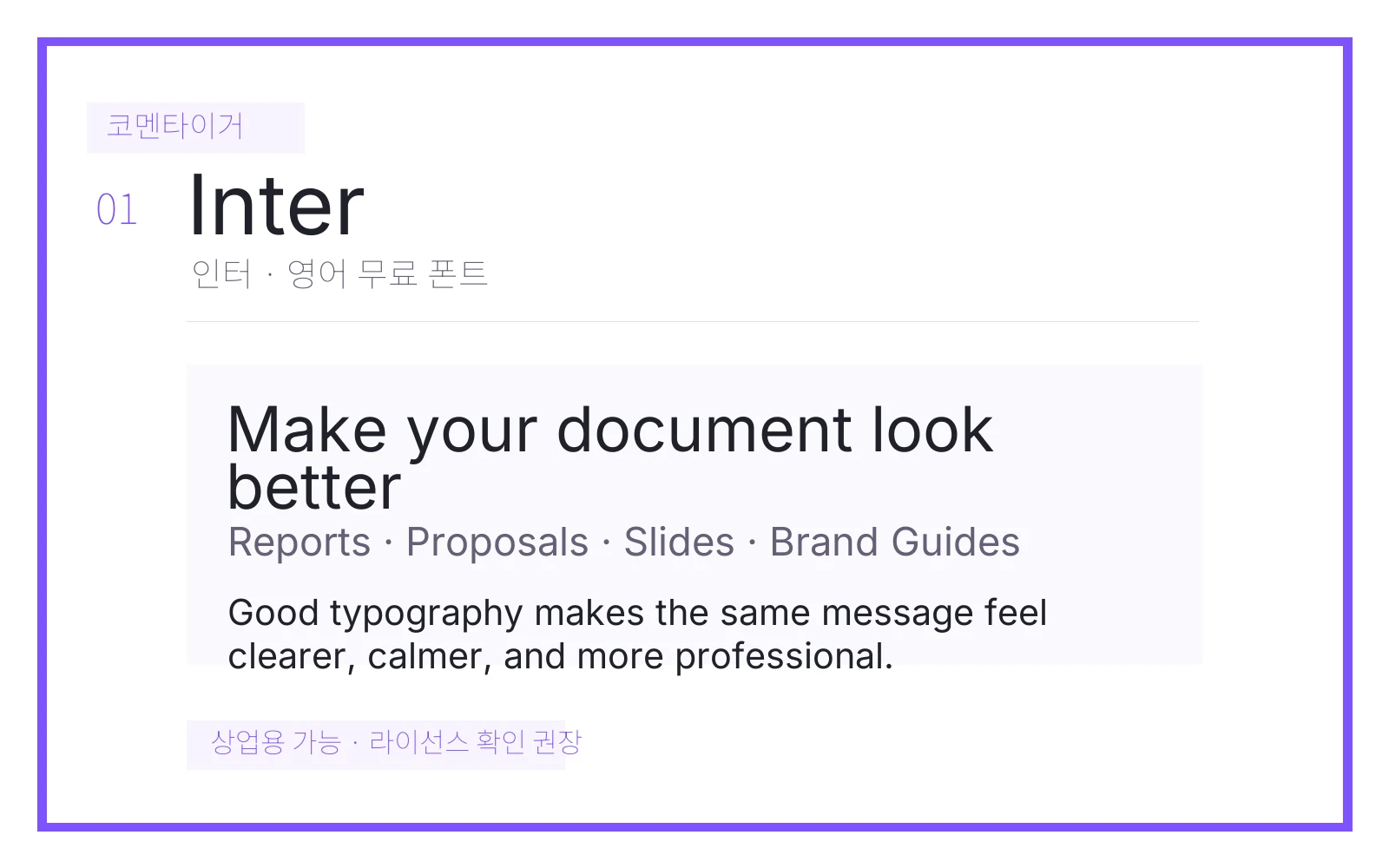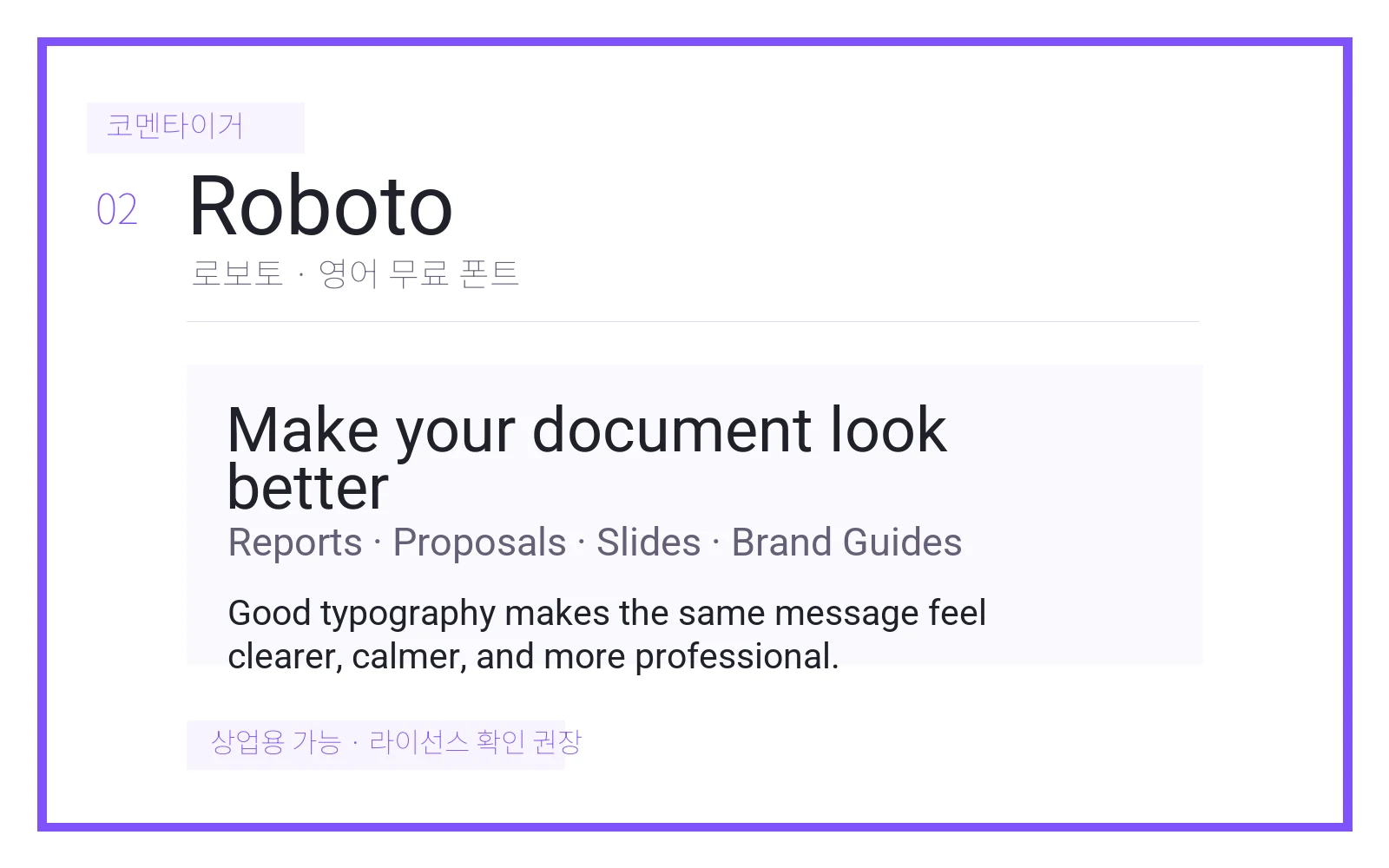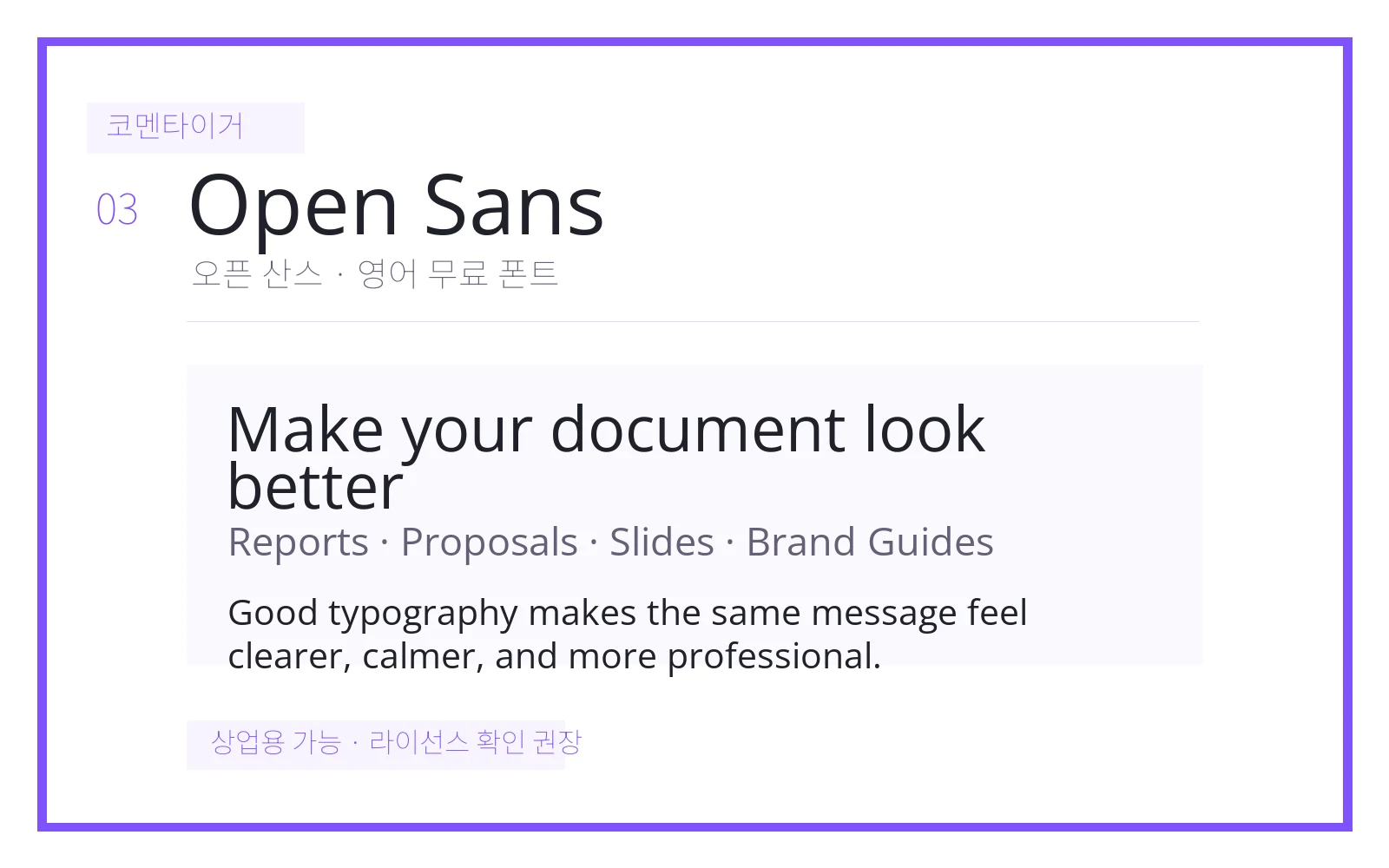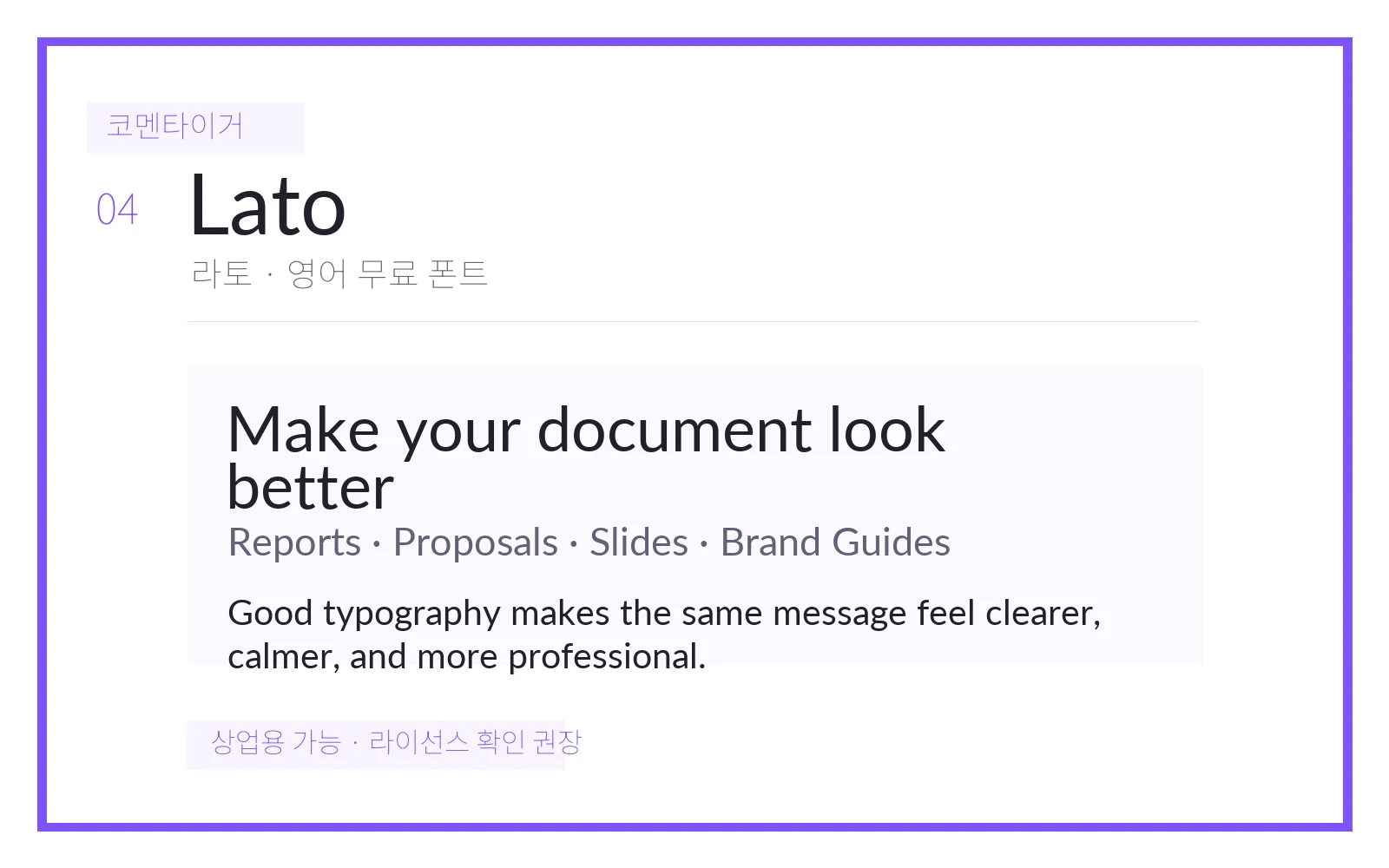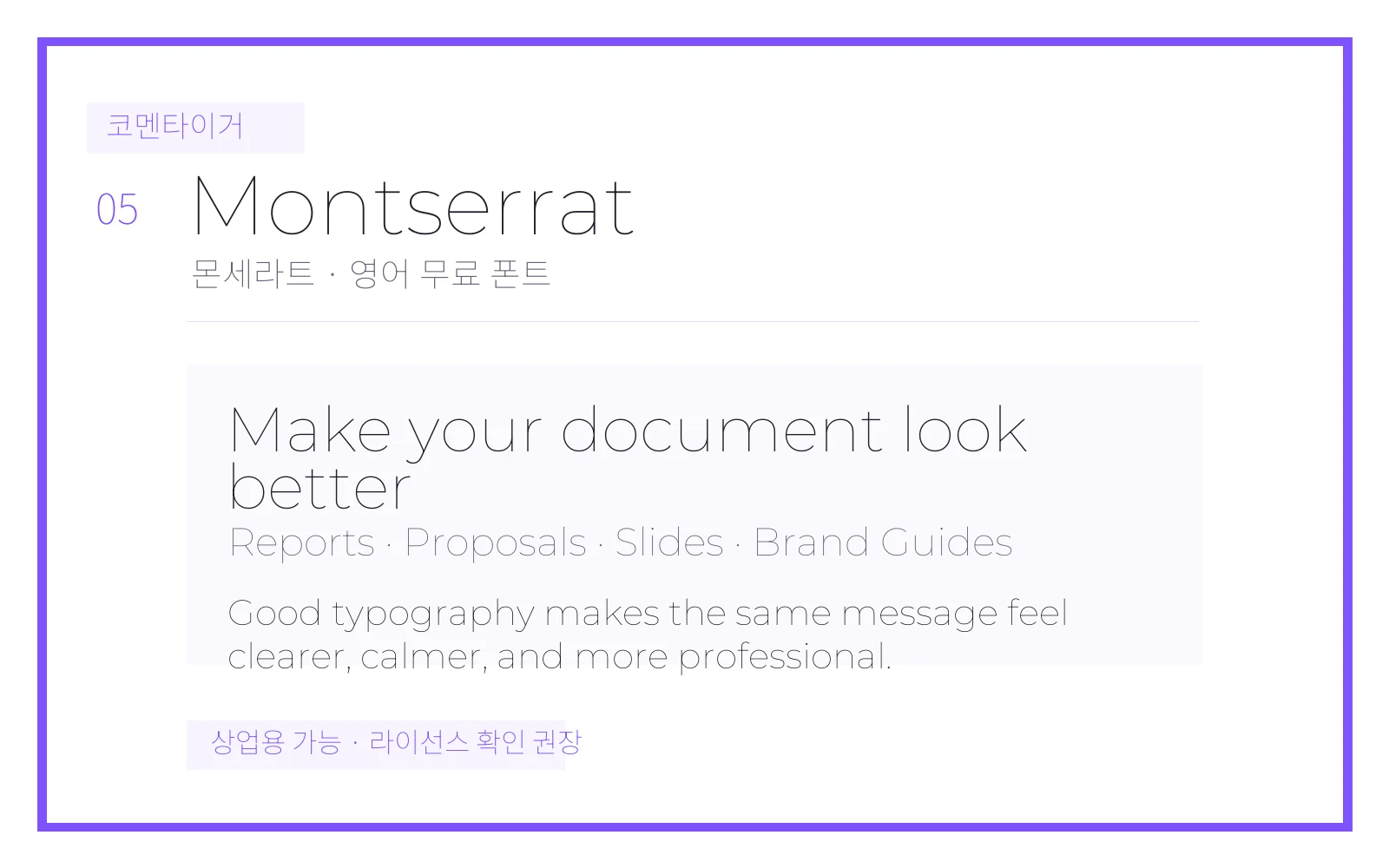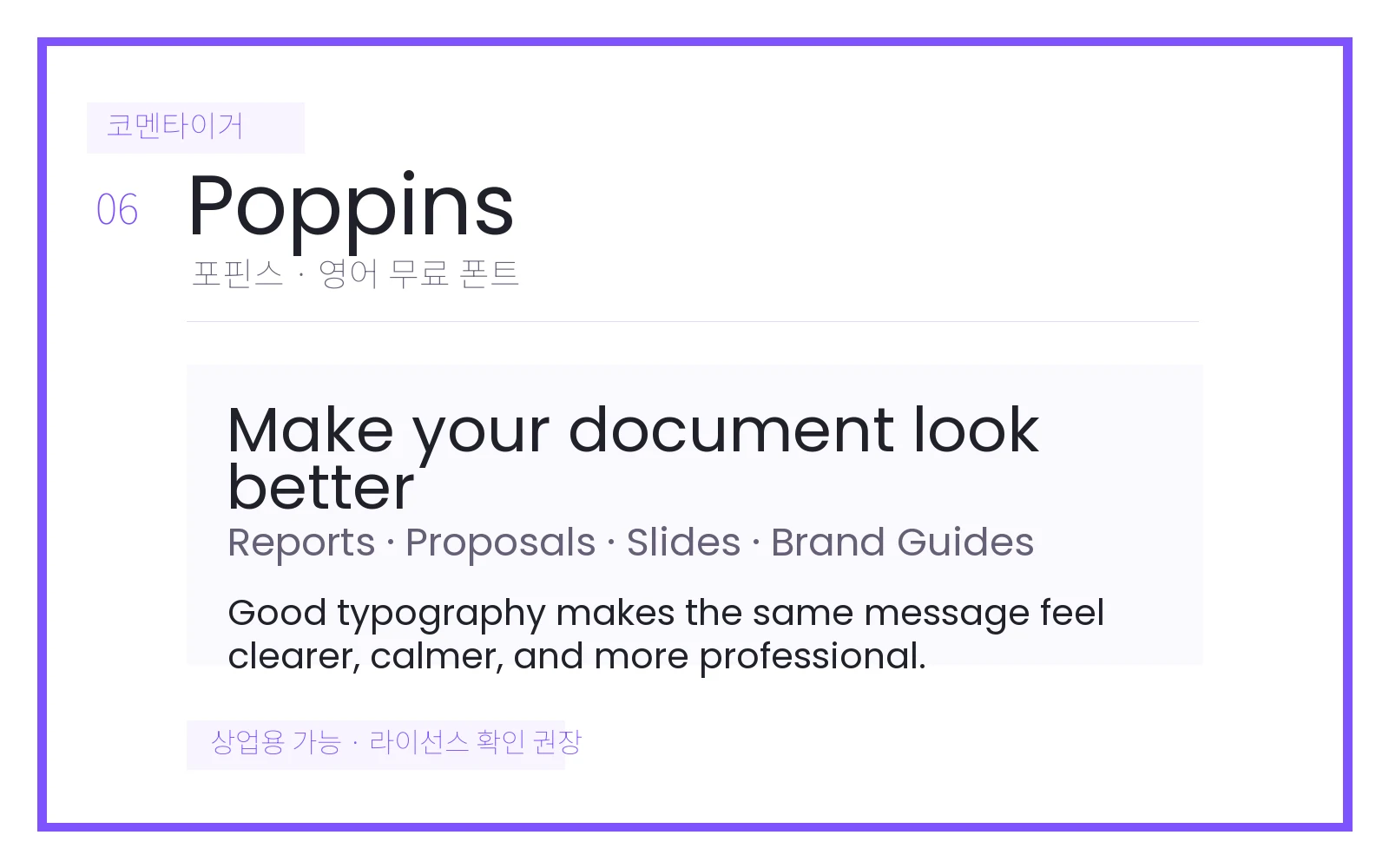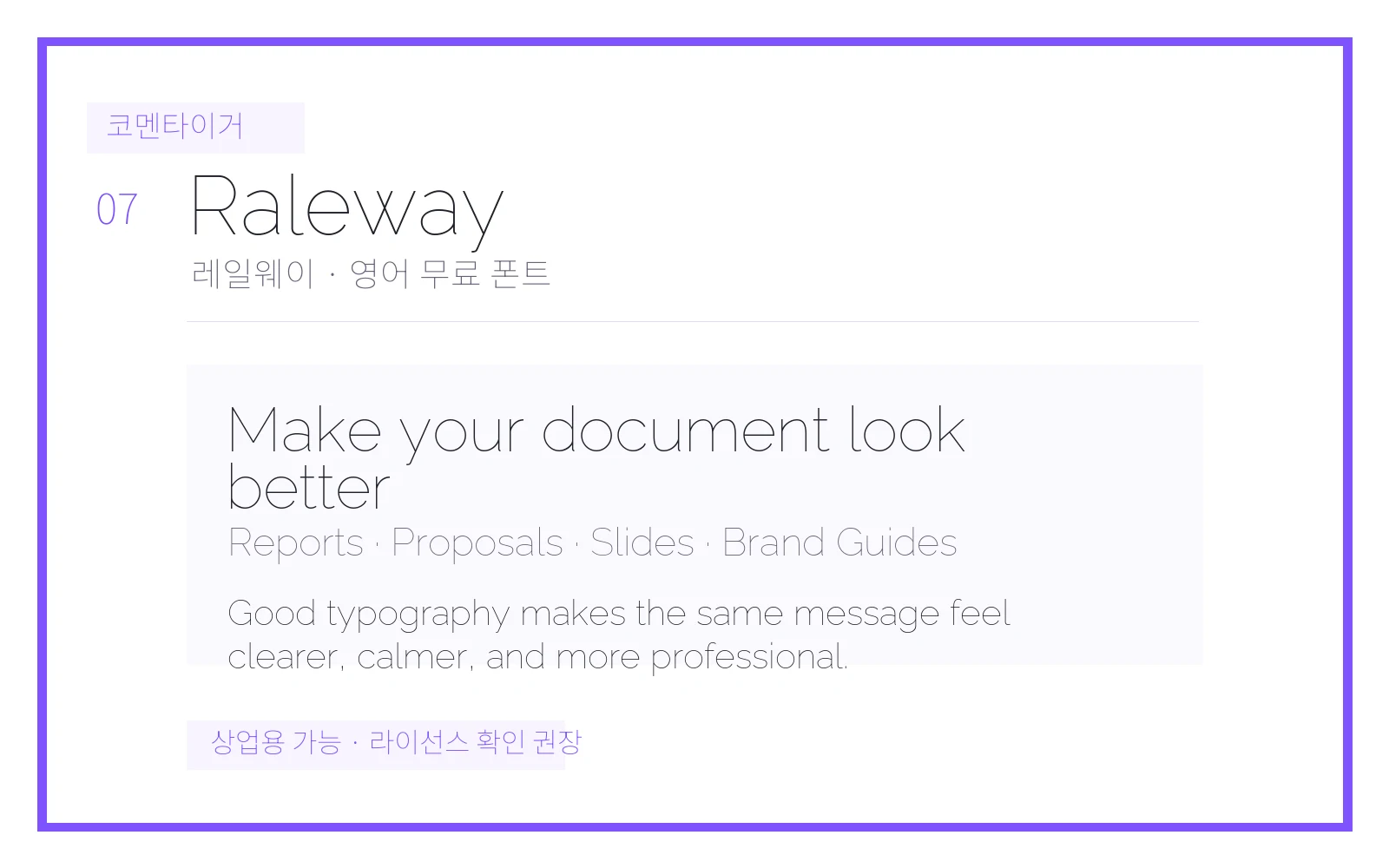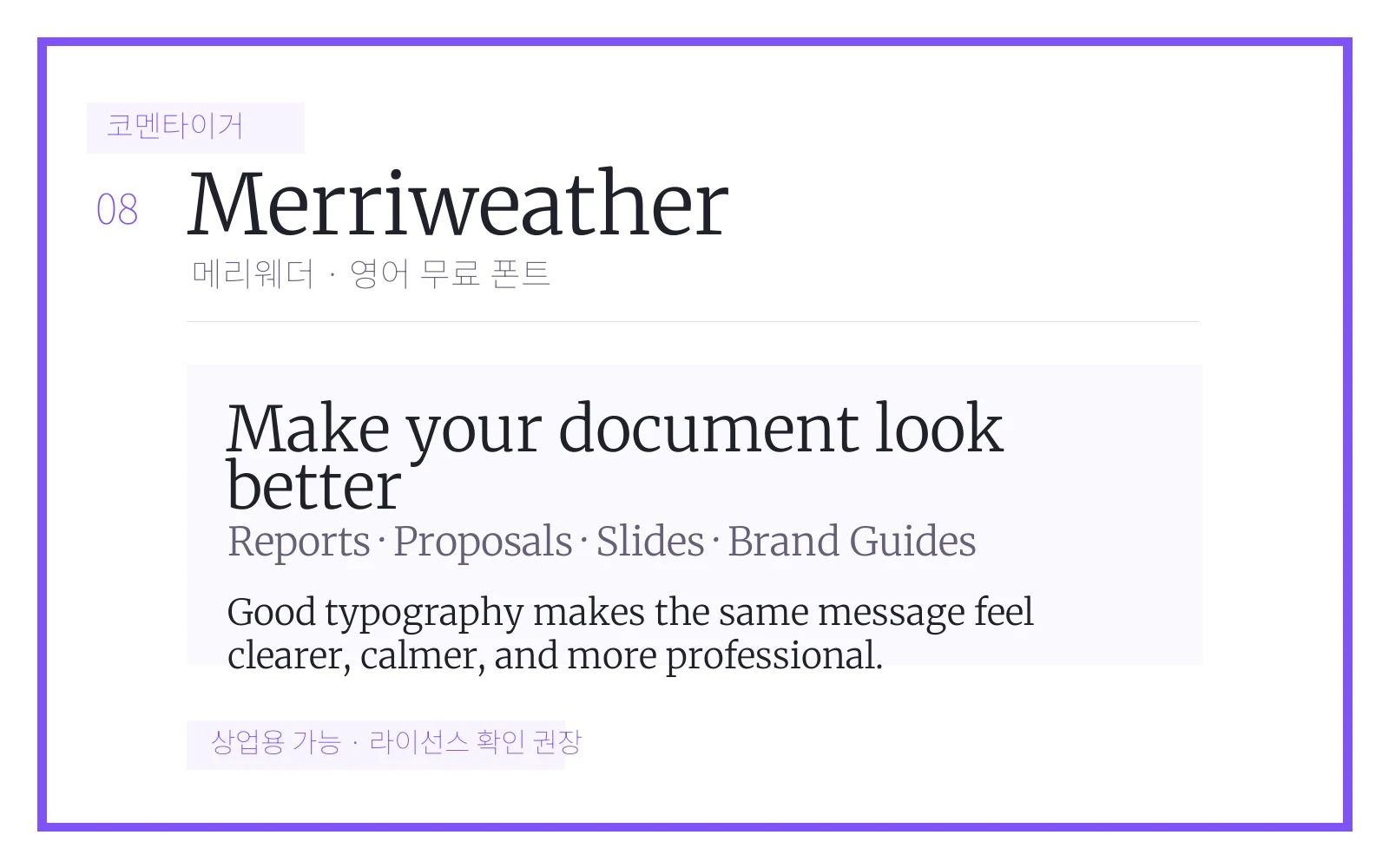
문서와 디자인에 쓰기 좋은 영어 무료 폰트 10개
영문이 들어간 보고서나 발표자료는 영어 폰트만 바꿔도 분위기가 크게 달라집니다. 한글 문서 안에 영어 제목, 제품명, 인용문이 자주 들어간다면 아래 폰트들을 몇 개 저장해두면 편합니다.
빠르게 고르는 기준
• 문서용 영문은 한글 폰트와 같이 썼을 때 높이와 굵기가 튀지 않는지가 중요합니다.
• 제목용은 개성이 있어도 좋지만, 본문용은 숫자·대문자·소문자가 오래 읽어도 편해야 합니다.
• 웹·앱·PPT를 함께 쓴다면 Google Fonts처럼 배포와 적용이 쉬운 폰트를 고르면 관리가 편합니다.
1. Inter
Inter 영어 무료 폰트 미리보기 이미지
Inter 미리보기. 출처: Google Fonts 공식 페이지
• 추천 용도: 앱, 보고서, 웹문서까지 두루 쓰기 좋은 현대적인 산세리프입니다.
2. Roboto
Roboto 미리보기. 출처: Google Fonts 공식 페이지
• 추천 용도: 구글 Material Design에서 익숙한 인상이라 UI 문서와 안내문에 안정적입니다.
3. Open Sans
Open Sans 미리보기. 출처: Google Fonts 공식 페이지
• 추천 용도: 작은 크기에서도 읽기 쉬워 긴 영문 본문과 웹페이지에 좋습니다.
4. Lato
Lato 미리보기. 출처: Google Fonts 공식 페이지
• 추천 용도: 딱딱하지 않으면서도 단정해서 회사 소개서나 제안서에 잘 어울립니다.
5. Montserrat
Montserrat 미리보기. 출처: Google Fonts 공식 페이지
• 추천 용도: 제목용 존재감이 좋아 포스터, 표지, 발표자료 타이틀에 적합합니다.
6. Poppins
Poppins 미리보기. 출처: Google Fonts 공식 페이지
• 추천 용도: 둥글고 깔끔한 느낌이라 카드뉴스와 서비스 소개 자료에 편합니다.
7. Raleway
Raleway 미리보기. 출처: Google Fonts 공식 페이지
• 추천 용도: 얇은 제목이나 브랜드 무드가 필요한 표지에 세련된 느낌을 줍니다.
8. Merriweather
Merriweather 미리보기. 출처: Google Fonts 공식 페이지
• 추천 용도: 긴 영문 글을 읽기 좋게 만드는 세리프 폰트라 리포트 본문에 좋습니다.
9. Playfair Display
Playfair Display 미리보기. 출처: Google Fonts 공식 페이지
• 추천 용도: 고급스러운 제목용 세리프라 초대장, 브로슈어, 표지에 잘 맞습니다.
10. Source Serif 4
Source Serif 4 미리보기. 출처: Google Fonts 공식 페이지
• 추천 용도: 논문, 보고서, 긴 설명문처럼 차분한 영문 본문에 적합합니다.
짧게 고르는 기준
• 보고서·웹문서 본문: Inter, Roboto, Open Sans, Lato
• 발표자료·표지 제목: Montserrat, Poppins, Raleway
• 고급스러운 긴 글·브로슈어: Merriweather, Playfair Display, Source Serif 4
영어 폰트는 한글 폰트와 섞어 쓰는 일이 많기 때문에, 너무 개성이 강한 폰트보다는 제목용과 본문용을 나눠서 고르는 편이 안정적입니다.
용도별 추천 정리
• 보고서·앱 화면: Inter, Roboto, Open Sans
• PPT 제목·랜딩 페이지: Montserrat, Poppins, Raleway
• 차분한 인용문·브랜드 문구: Merriweather, Playfair Display, Source Serif 4